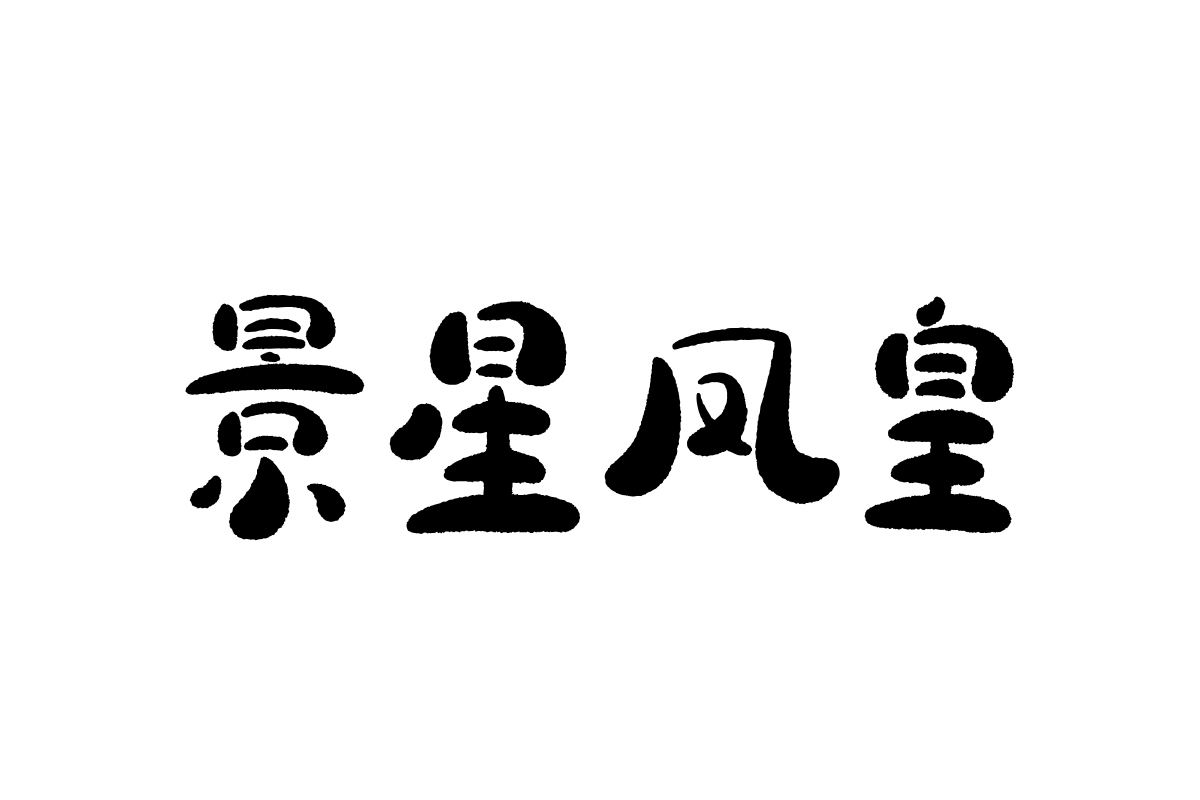
汉仪熊猫体是一款非常受欢迎的中文字体,由汉仪字库开发。这款字体以其独特的设计和可爱的形象深受广大用户的喜爱。
汉仪熊猫体的笔画流畅,字形圆润,给人一种亲切、可爱的感觉。它的结构简洁明了,易于阅读和书写。无论是用于书籍、报纸、杂志还是网页设计,都能展现出其独特的魅力。
此外,汉仪熊猫体还具有很好的可读性,适合用于各种正式场合的书写和打印。它的字体大小和间距可以根据需要进行调整,使得文字更加清晰易读。